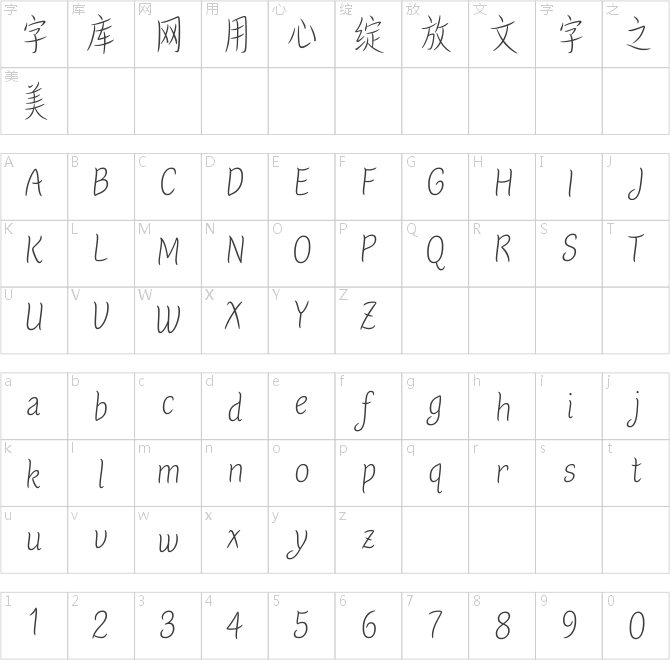
漢儀淺光的筆畫全部由細膩生動的弧線組成,所有筆勢均向右提收,猶如被微風吹拂著的柳葉般充滿生機,字形風格統一,帶給人一種清雅、秀麗的視覺感受。
漢儀淺光 W字體HYQianGuangW字庫是一款讓人賞心悅目、百看不厭的中文字體,適合各類廣告和產品包裝設計應用,字體大小7.19MB,格式為ttf字體,上傳用戶是董志高,作者/版權方為漢儀字庫